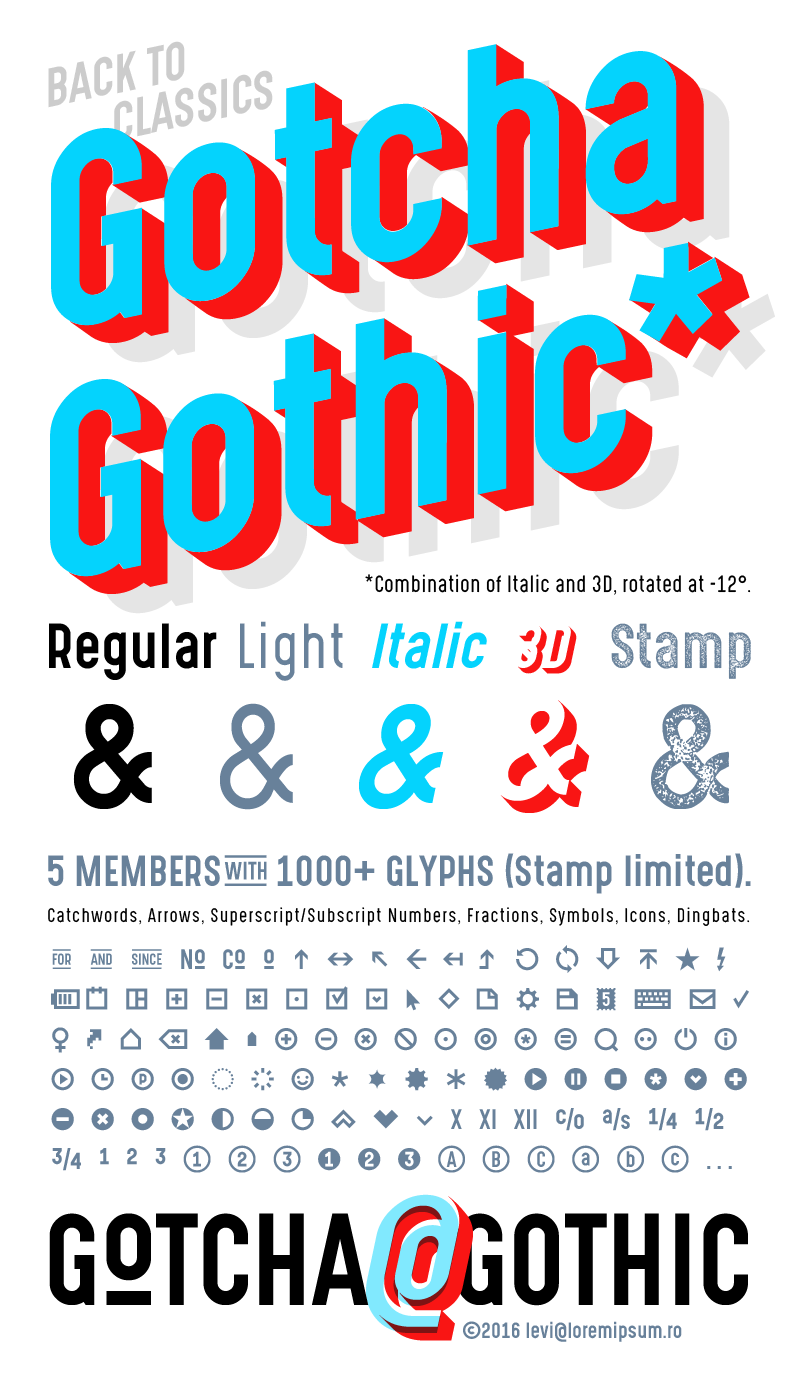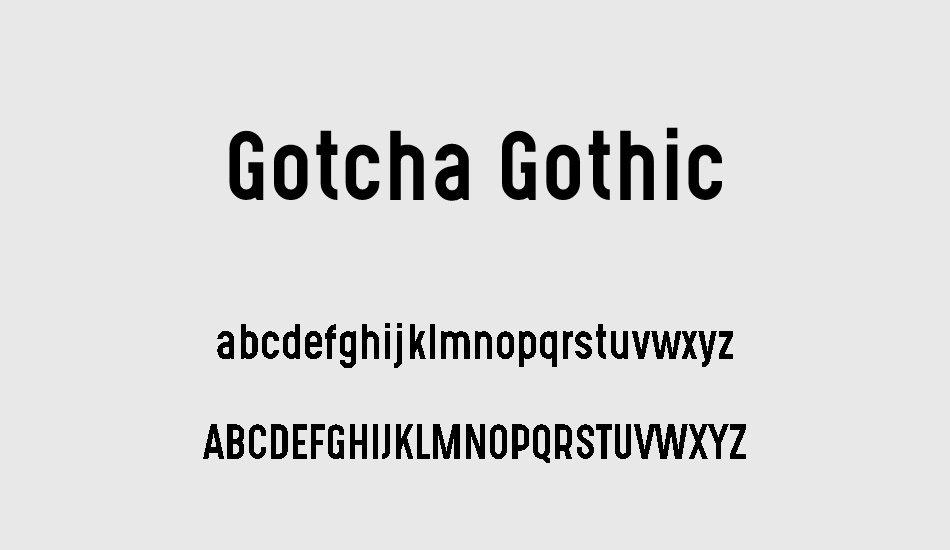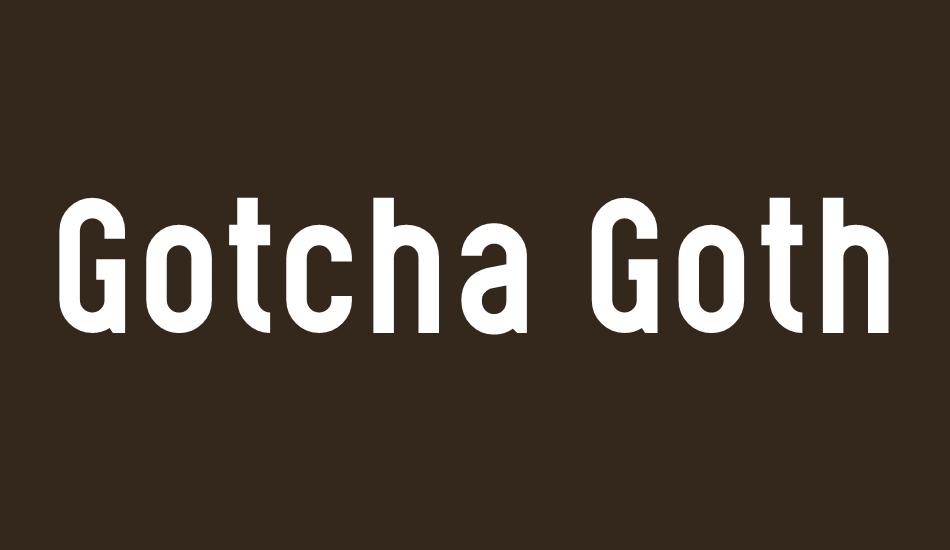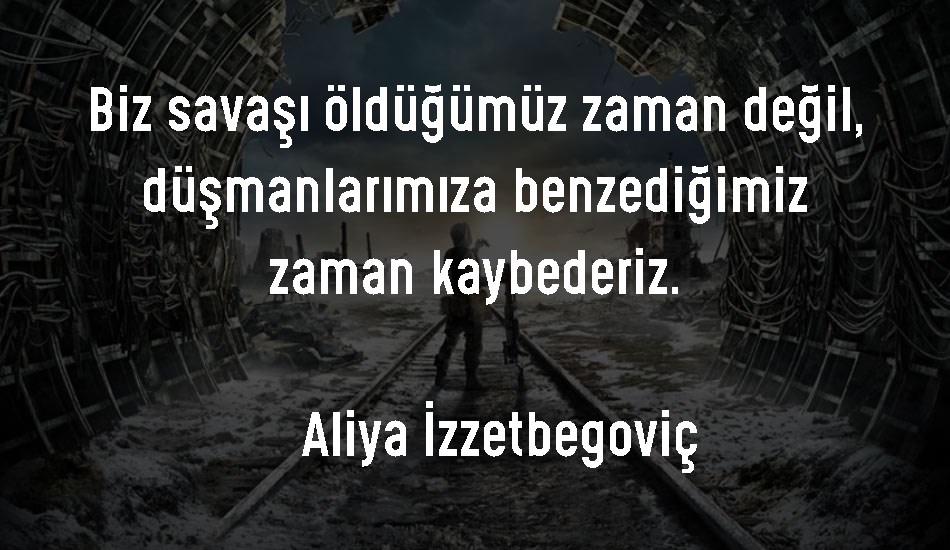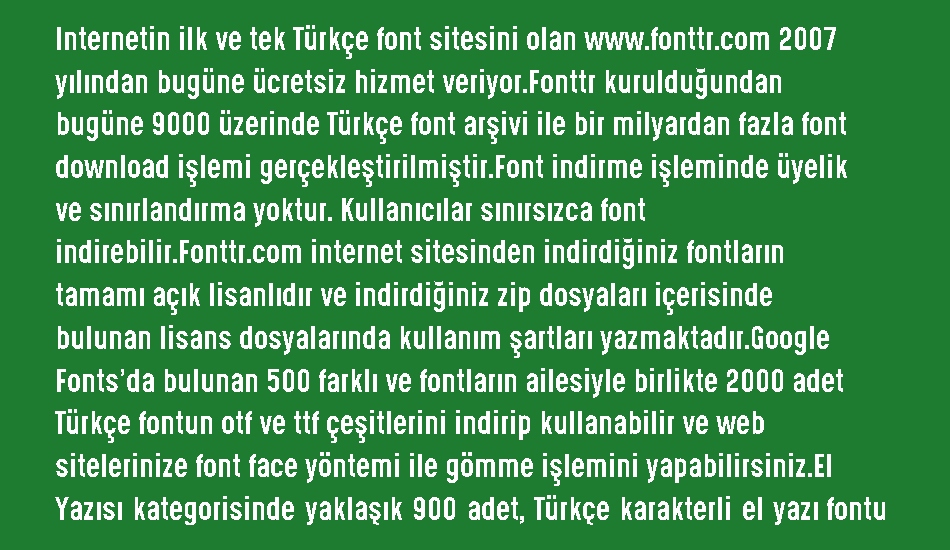
Klasiklere kişisel bir yaklaşım olan Gotcha Gothic, alt kategoriler, vurgular ve ikonografi içeren, web için değil, başlıklar için genişletilmiş bir seçeneğe sahip olmak için yaratılmıştır. Optik ayarlamalar ve grafik efektleri, bir blok, cesur bir görünüm için en aza indirildi (bir Franklin'den daha fazla bir Etki).
Mektupların potansiyel örtüşmesini örtmek ve doğru bir etki bırakmak için 3D versiyonu İtalik ile birlikte kullanılmalıdır. 3D, geniş bir karakter aralığıyla olsa da İtalik'e ihtiyaç duymayabilir.
Stamp Basic, daha küçük bir dosya boyutu tutmak için azaltılmış bir karakter miktarına sahiptir, genişletilmiş versiyonun Regular'ın tüm gliflerine sahip olmasına karşın, bir font için aşırı büyük bir boyuta ulaşmaktadır.